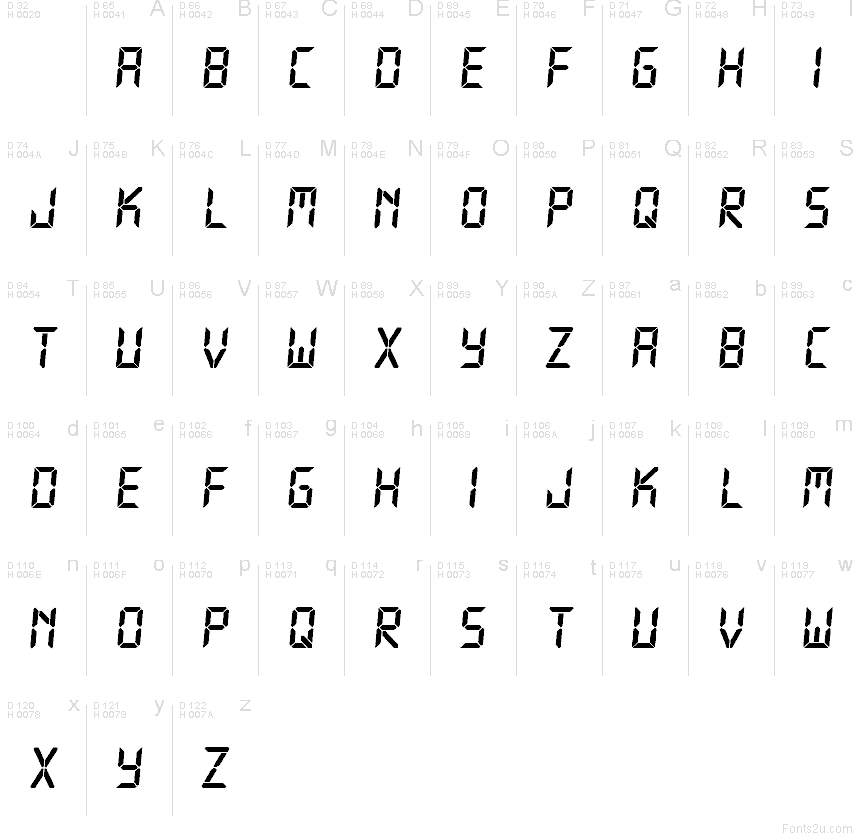
Technology Extravagant Italic di Vladimir Nikolic è un font display digitale gratuito, composto da tratti poligonali segmentati che richiamano i display LED e gli indicatori strumentali. I tagli bisellati ricorrenti e le parti separate simili a barre conferiscono ai caratteri un ritmo meccanico, facendoli apparire più come pezzi di segnaletica assemblati che come un normale carattere display.
Questa struttura è perfetta per titoli di videogiochi, poster di eventi tecnologici, branding ispirato alle interfacce, copertine di album e grafiche per streaming, dove un look numerico e sistemico aiuta a definire l'atmosfera. Conferisce inoltre molta incisività a etichette brevi, intestazioni stile tabellone segnapunti e packaging sci-fi, soprattutto quando si desidera che siano le interruzioni angolari a creare l'impatto visivo, evitando effetti superflui.